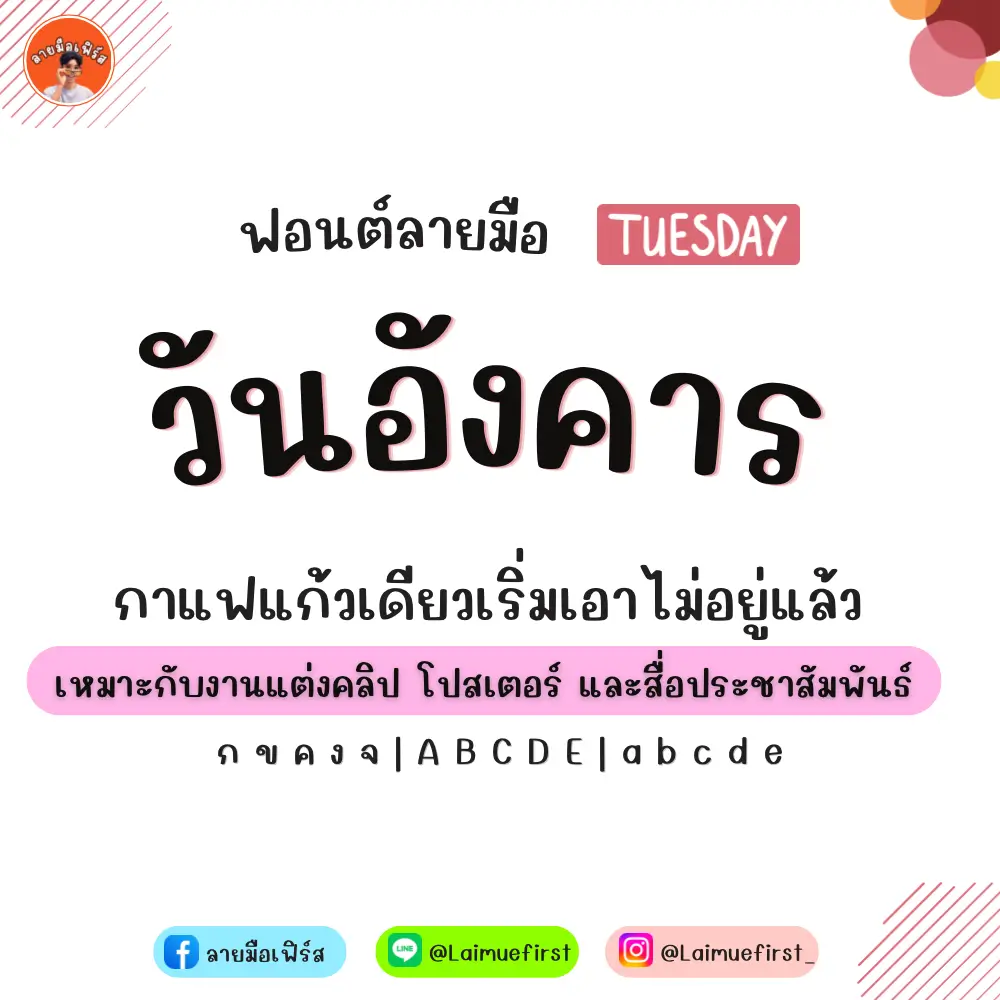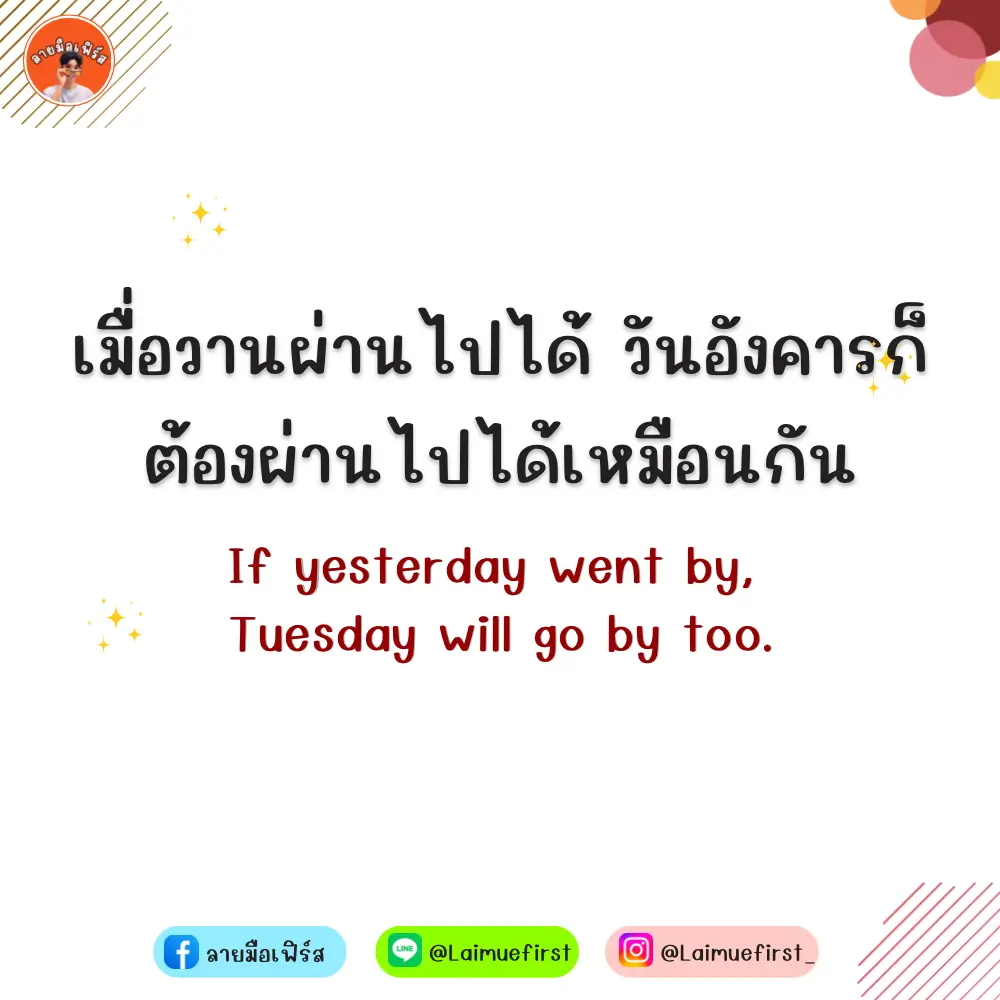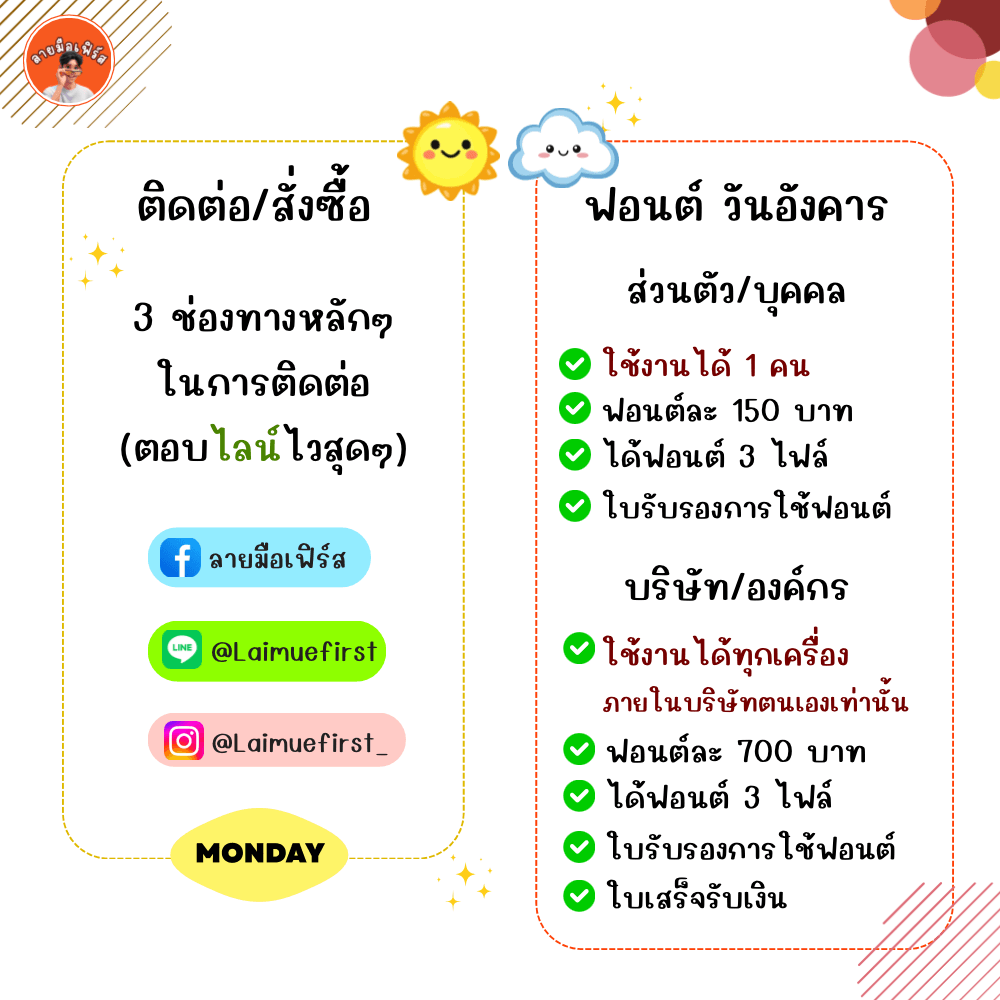
ฟอนต์วันอังคาร (LMF Wanangkhan) – แจกฟรีสำหรับทดลองใช้งานแบบส่วนตัว เวอร์ชันทดลอง (Demo)
- ตัวหนังสือโปร่งปนกับตัวปกติ
- ตัวหนังสือปกติ ไม่มีตัวโปร่งปน